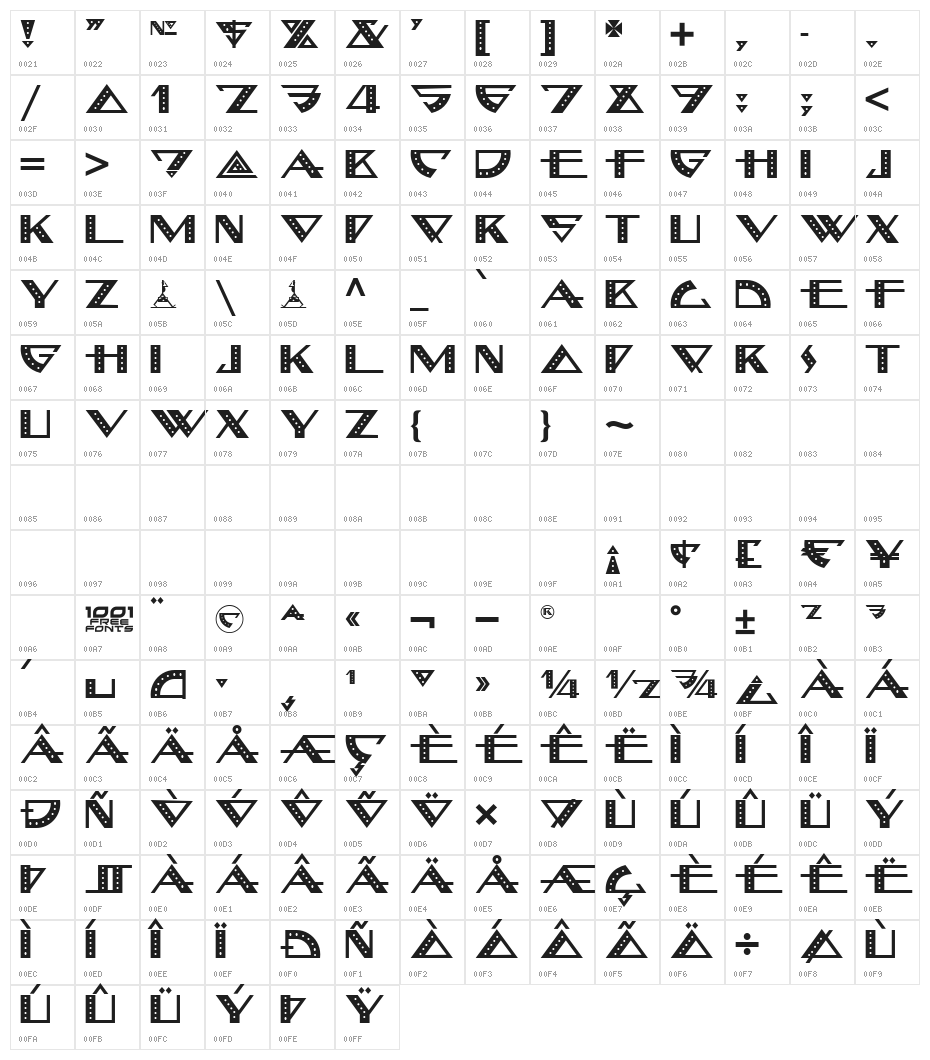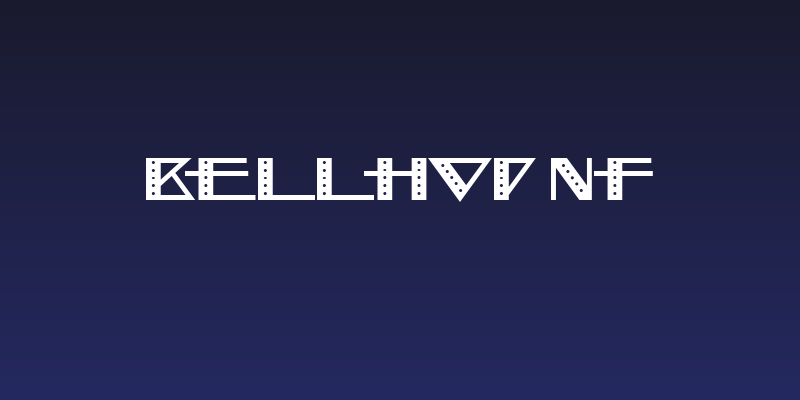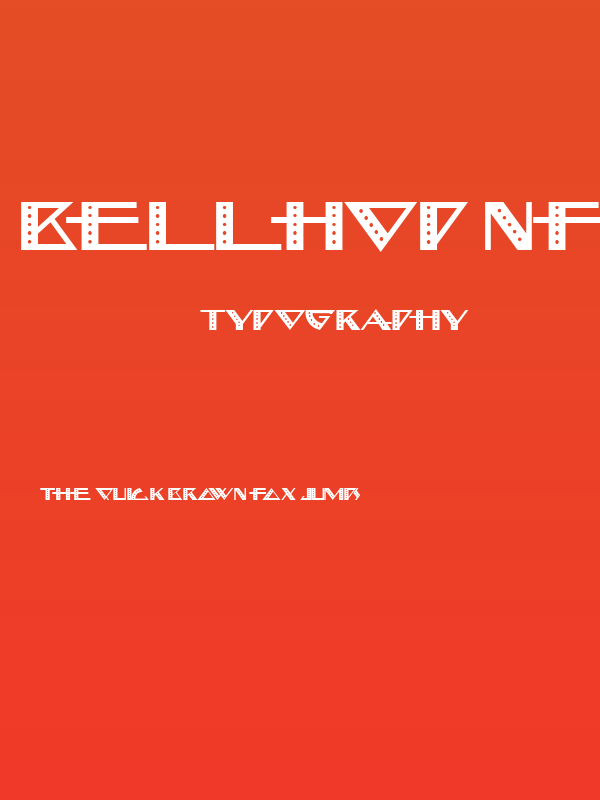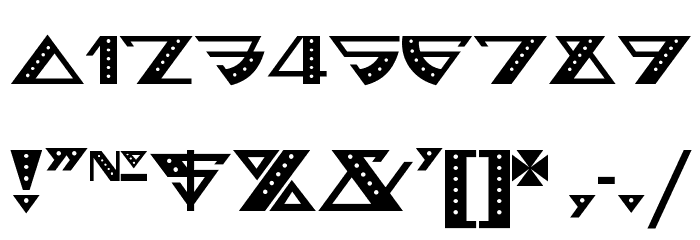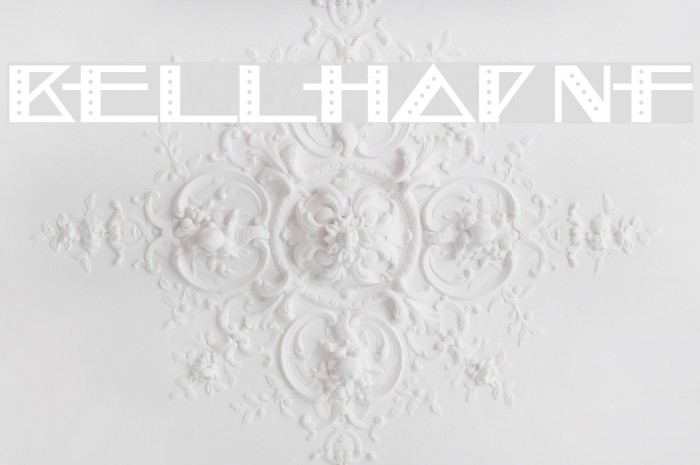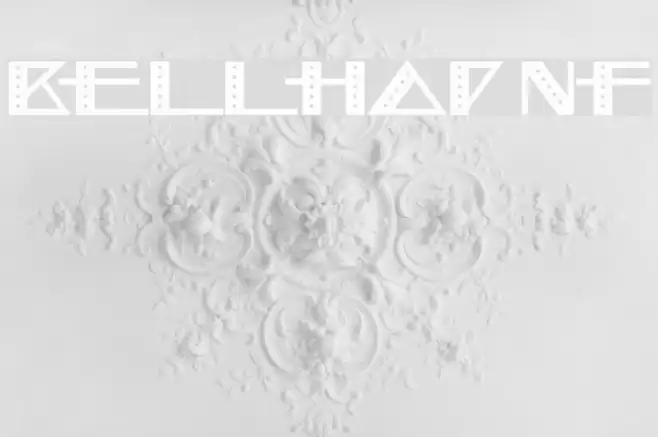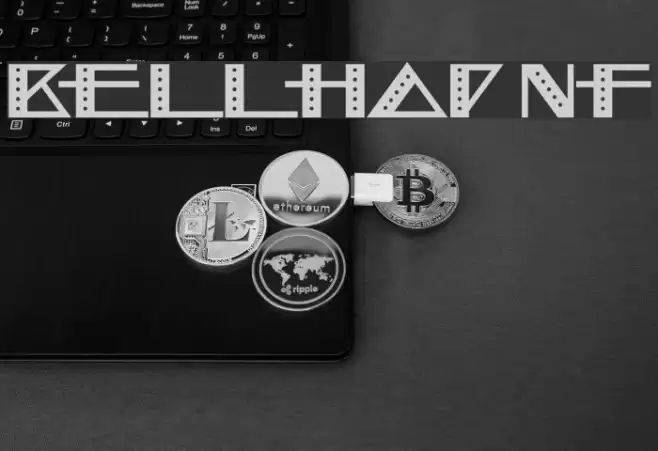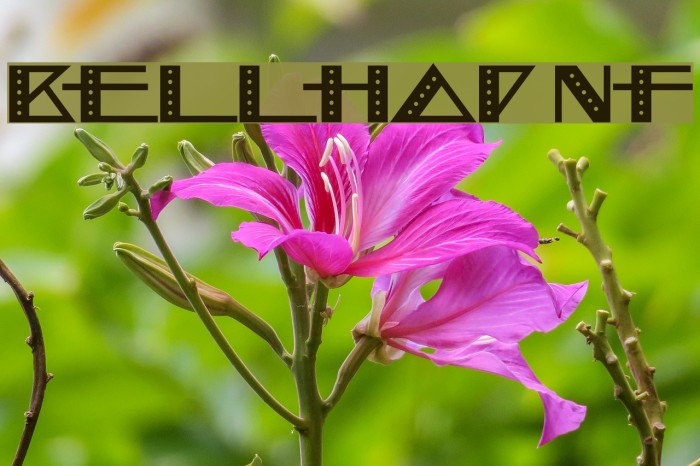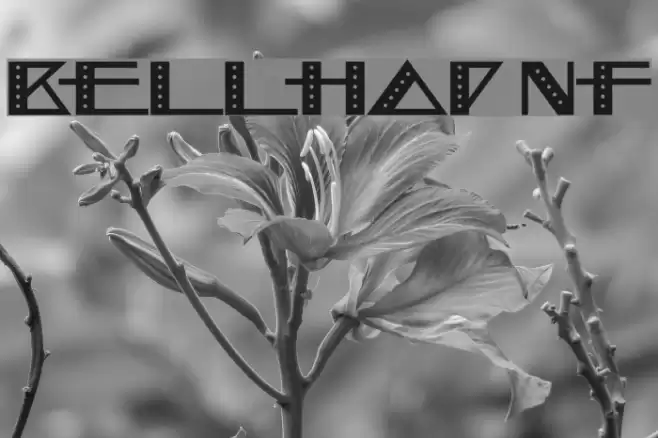
Bellhop NF Font
| Gesamtstil | Modern, Decorative |
| Vorgeschlagene Projekte | Ideal for branding, posters, album covers, and any design needing a bold, modern touch. |